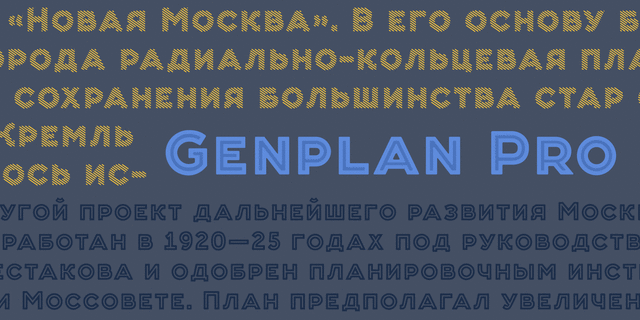
About Genplan ProГенплан Про – это акцидентное шрифтовое семейство из девяти типографических слоев с ярким историческим характером. Начертания этого семейства могут использоваться как в спайке, один поверх другого, так и отдельно. Генплан Про основан на рисунке названия генерального плана Москвы 1935 года. Шрифт поддерживает все европейские алфавиты, включая греческий, и все кириллические алфавиты, включая азиатские, содержит знаки верхнего регистра и капитель. Также в набор входят знаки российского рубля, украинской гривны и казахского тенге. Шрифт содержит множество альтернативных глифов, украинские традиционные лигатуры, дискретные лигатуры, языковые альтернативы для польского (черточка), албанского (форма буквы J), и болгарского (треугольные Д и Л). Генплан Про создан для акцидентного использования, а значит отлично подойдет для логотипов, заголовков и буквиц. Шрифт разработан Дмитрием Голубом и выпущен в студии Thundertype в 2014 году.
Associations for font family Genplan ProTypeface personality and character:
heavy, strong, powerful, convincing, loud, self-assured, durable, rude, manly, brutal, accurate, flat, solid, iron, steel, cutting, crisp, logical, cold, workman, industrial, schematic, urban, urbanistic, automatic, engineering, static, stable, reliable, reputable, serious, severe, technical, formidable, splashy, notable, dense, motivating, machine, technogenic, tough, ambitious, Vintage, game, hipster, thin, simple
mechanical engineering, security, fitness equipment, truck, trucker, power station, energy industry, building, industry, architecture, architect, engineer, city, urban studies, machine tool, factory, constructor, game, brick, automation, scheme, steel-maker, robot, design, equipment, steam locomotive, port, safe, repairs, protection, airsoft, construction, footwear, packing, excavator, tank, army, blockbuster, thriller, action, motor, engine, technology, workman, tool, car, railway, cubes, lego, oil, selfie, device, metallurgy, coworking Typeface associated with age: